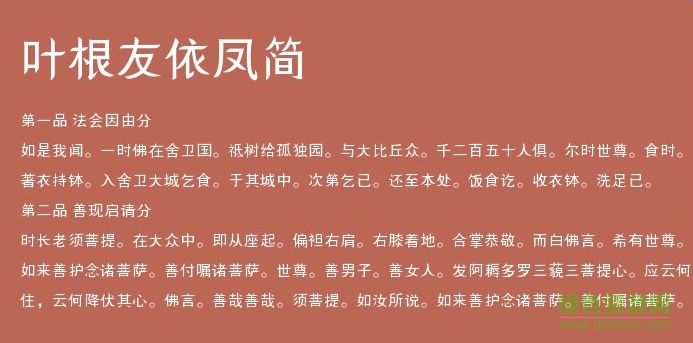
葉根友依鳳簡(jiǎn)字體是一款葉根友類優(yōu)雅簡(jiǎn)約風(fēng)格字體軟件,依鳳簡(jiǎn)體盡顯清新文雅,字里筆畫間透露這一絲絲青春活力,字體筆畫行如流水,十分優(yōu)美,整體效果放浪不羈,綠色資源網(wǎng)為您提供更多好看字體下載!
葉根友依鳳簡(jiǎn)是一款時(shí)尚的柳葉彎眉式的漢字字體。喜歡漢字字體的朋友有福了,這款相信能入您的法眼,字與字之間一氣呵成,清晰簡(jiǎn)約脫俗,故取名葉根友依鳳簡(jiǎn)。
該字體盡顯漢典字的霸氣特點(diǎn),字體筆畫相互連接,看似雜亂卻不失基本工整,非常的文雅好看,是漢典字里面比較大方得體的了。